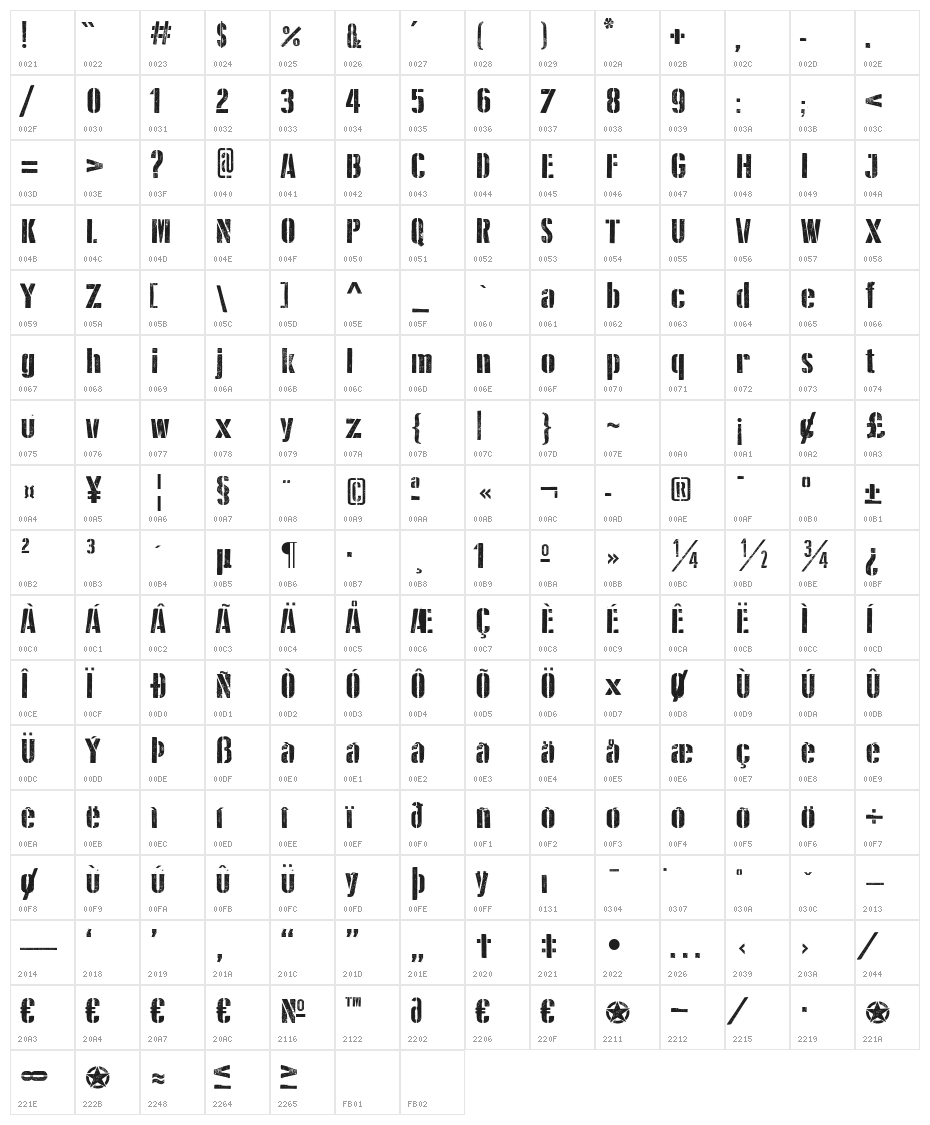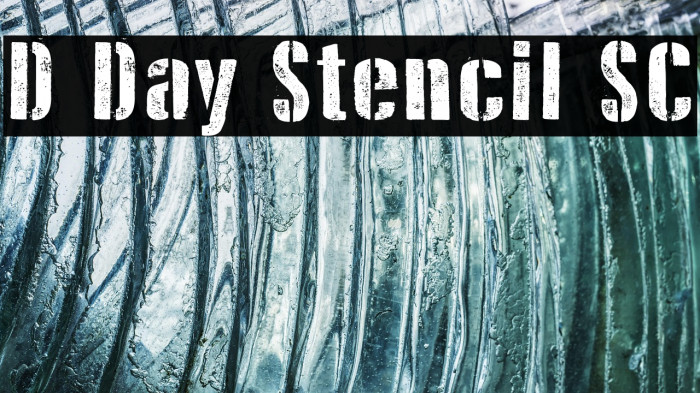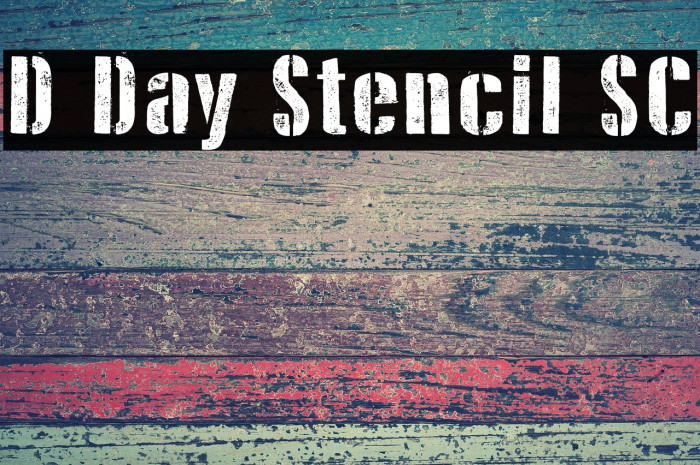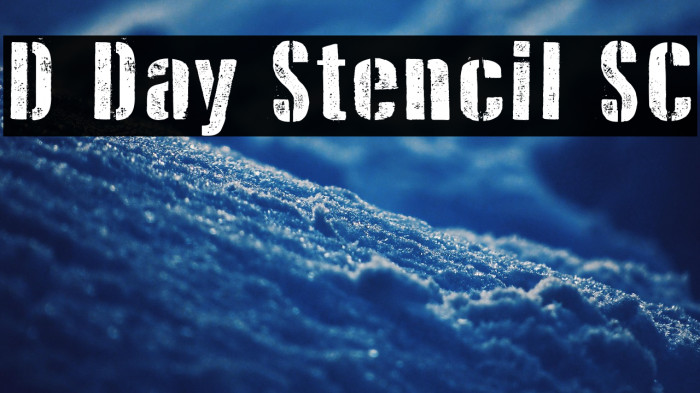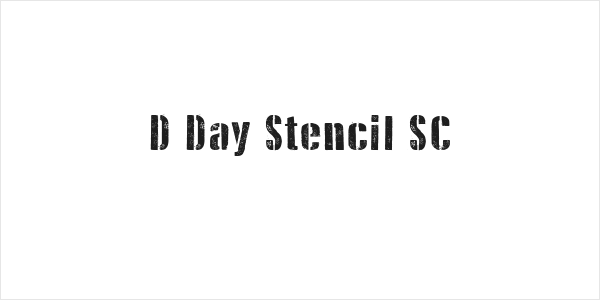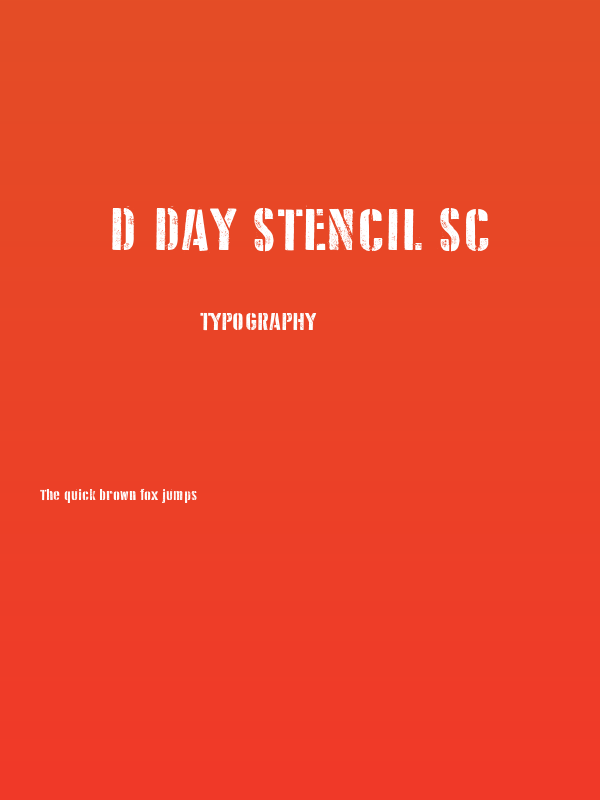
D Day Stencil SC Font
✎ Stencil
| Progetti proposti | Ideal for military-themed designs, posters, branding, and packaging that require a rugged, authentic look. |